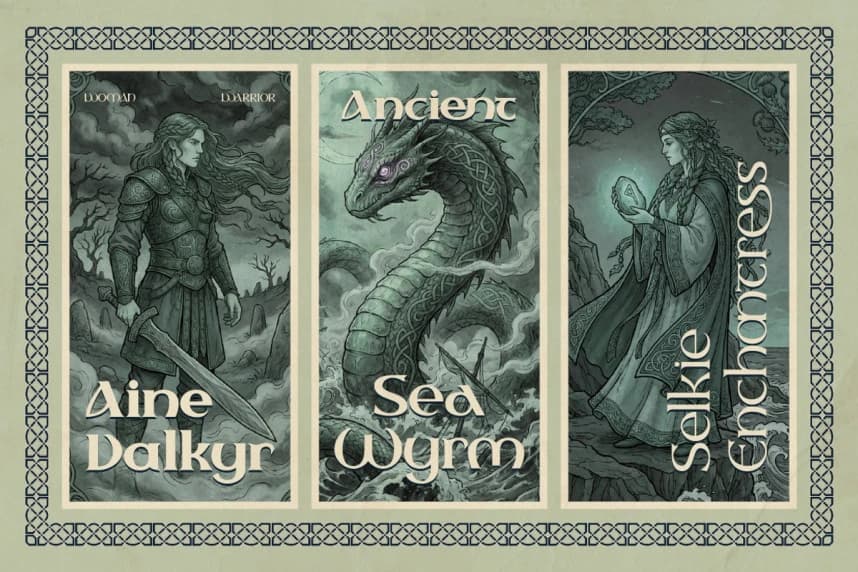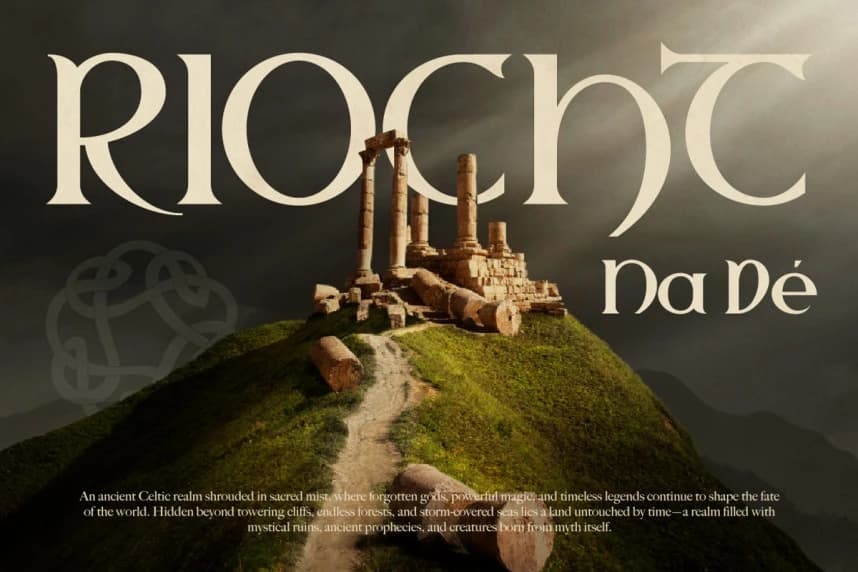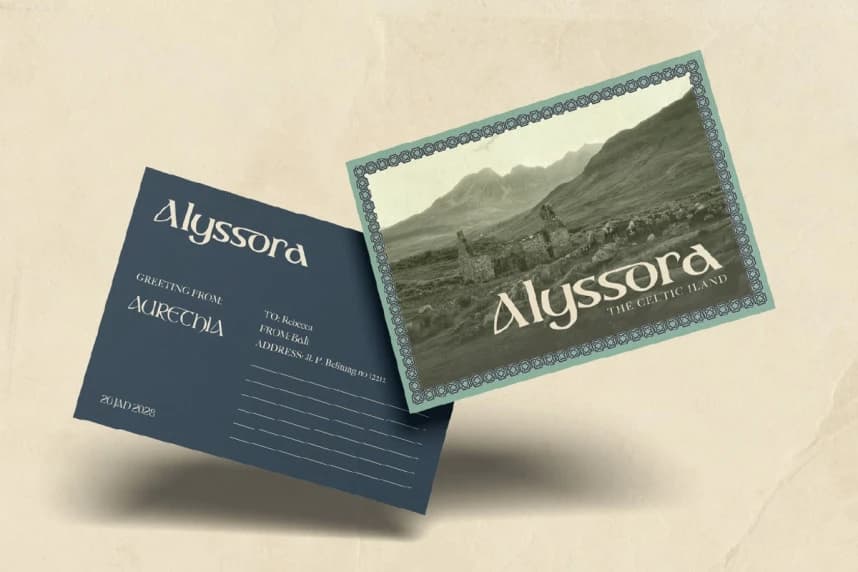
Sealgair Yazı Tipi
Sealgair Font güçlü ve zarif bir Keltik yazı tipi ailesidir; antik Norse ve Gaelic estetiklerinden ilham almıştır. Belirgin eğriler, keskin kenarlar ve süslemeli akış ile tasarlandı; bu yazı tipi mitoloji, savaşçılar ve zamansız efsanelerin ruhunu yakalar.
Sealgair Font, antik Norse ve Gaelik estetiklerinden ilham alan güçlü ve zarif bir Kelt yazı tipi ailesidir. Ayırt edici eğriler, keskin kenarlar ve süsleyici akışla tasarlanmış bu yazı tipi, mitolojinin, savaşçıların ve zamansız efsanelerin ruhunu yakalar.